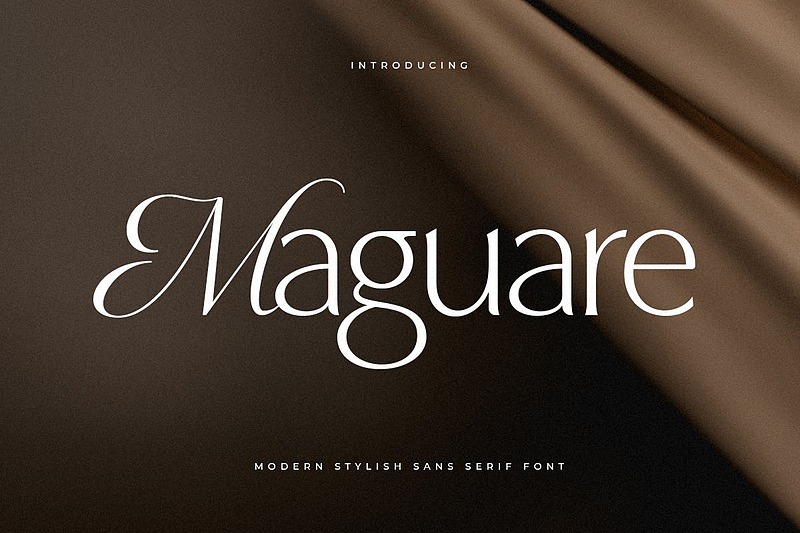
مَگوار، یک فونت مدرن و شیک سنس سریف است که همراه با یک فونت جفت رایگان ارائه میشود و پروژههای شما را به ظاهری لاکچری، الگانت، مدرن، مینیمالیستی، منحصربهفرد و باکلاس ارتقا میدهد. این فونت به طور خاص برای پروژههای مدرن و شیک طراحی شده و با دارا بودن کاراکترهای لیگچر زیبا و خوشفرم برای استفاده در مجلات، شبکههای اجتماعی، برندسازی، لوگو و موارد دیگر که نیاز به لمسهای مدرن و شیک دارند، آماده است.
استایلهای رگولار و ایتالیک
حروف کوچک و بزرگ
حروف چندزبانه
اعداد و علائم نگارشی
لیگچرهای زیبا و چشمنواز
طبقهبندی: سنس سریف
فاصلهگذاری: نرمال
اندازه بهینه: هر اندازهای